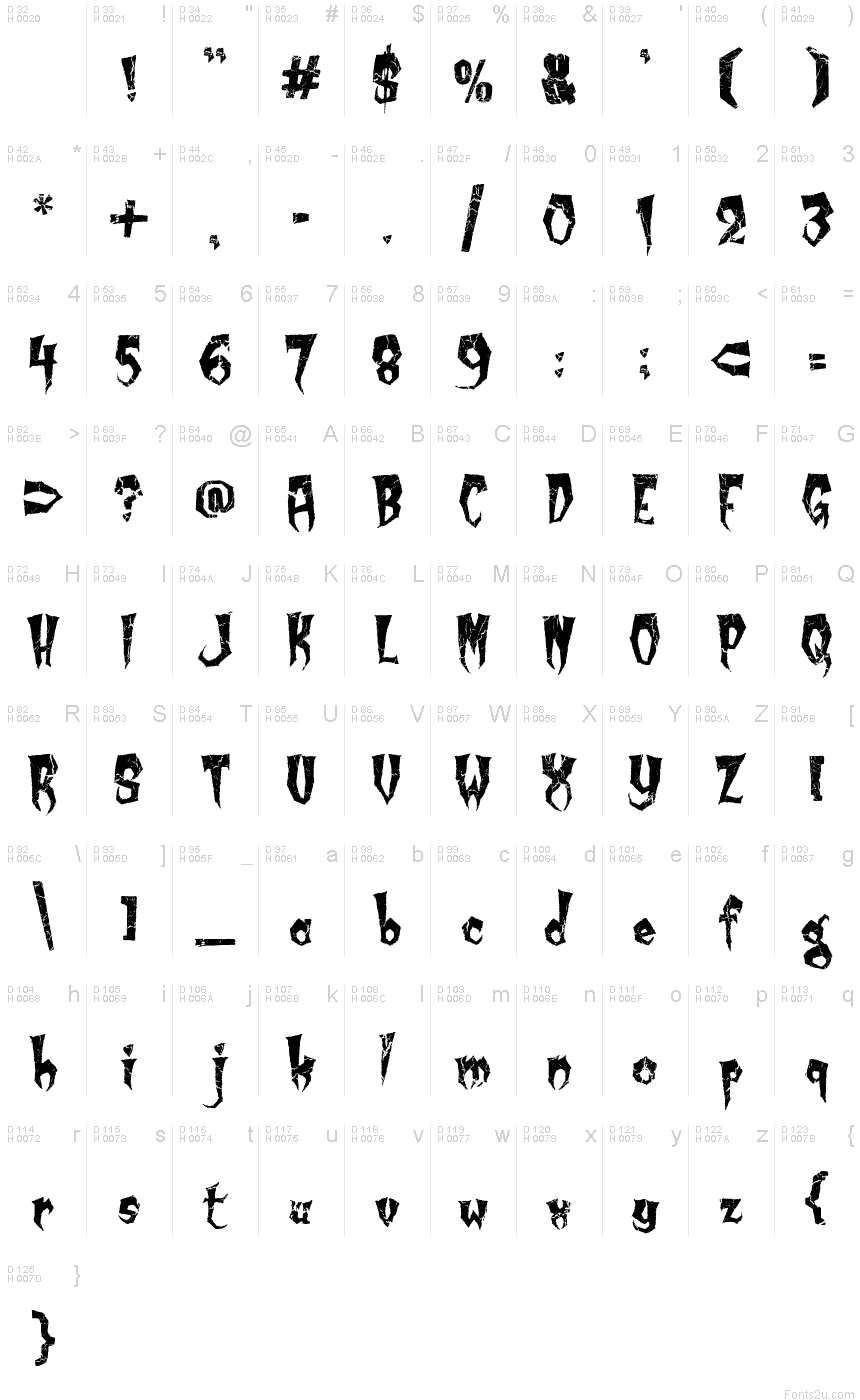
Kreepy Krawly di Chad Savage è un font horror display gratuito, caratterizzato da tratti lacerati, scheggiati e bordi ruvidi che ricordano delle artigliate. Le lettere appaiono graffiate e irregolari, conferendo al carattere una texture tesa e scolpita a mano, perfetta per un branding inquietante senza scadere nel cartoonesco.
Kreepy Krawly è ideale per locandine di Halloween, titoli di film horror, volantini per case stregate, grafiche per videogiochi e eventi a tema dark, poiché i suoi contorni spezzati trasmettono un senso di inquietudine e degrado anche nei testi brevi. Si adatta bene anche a packaging, merchandising e dettagli di loghi, quando il design richiede un tocco scritto a mano irregolare anziché una finitura liscia e pulita.